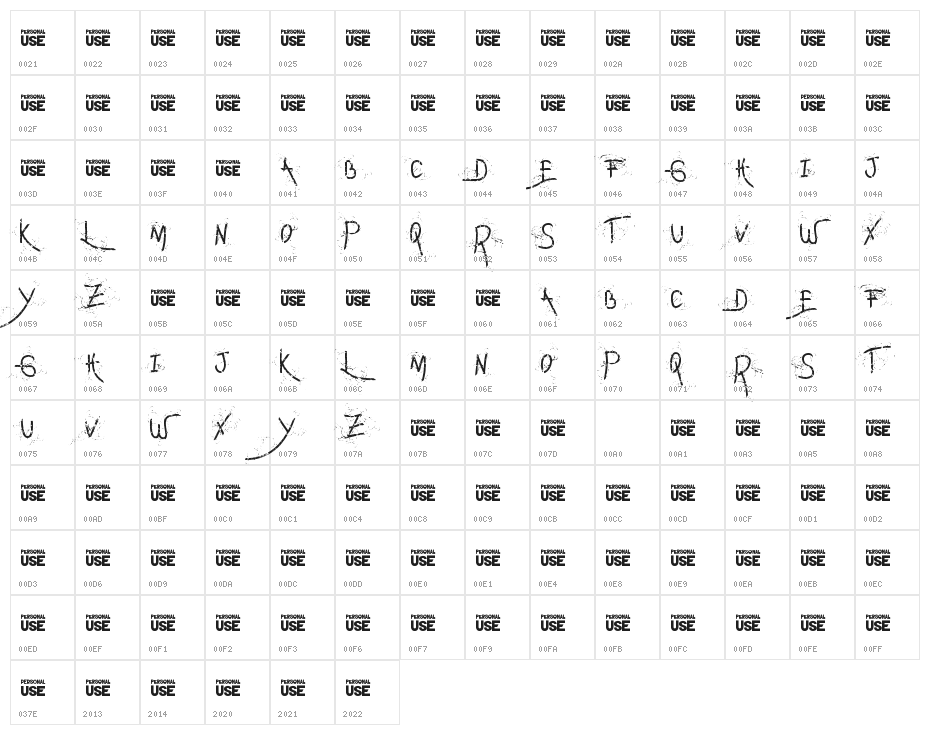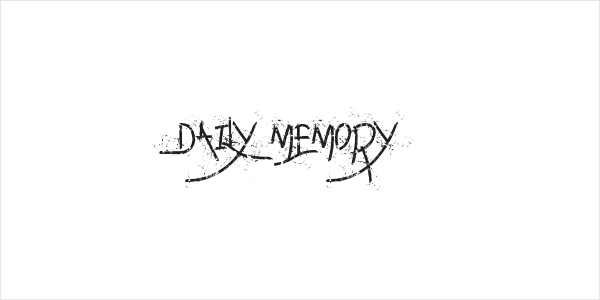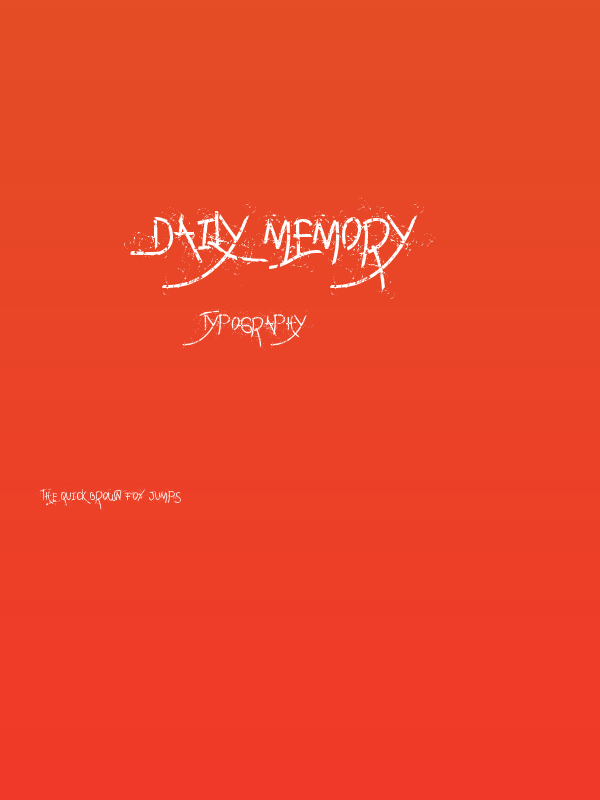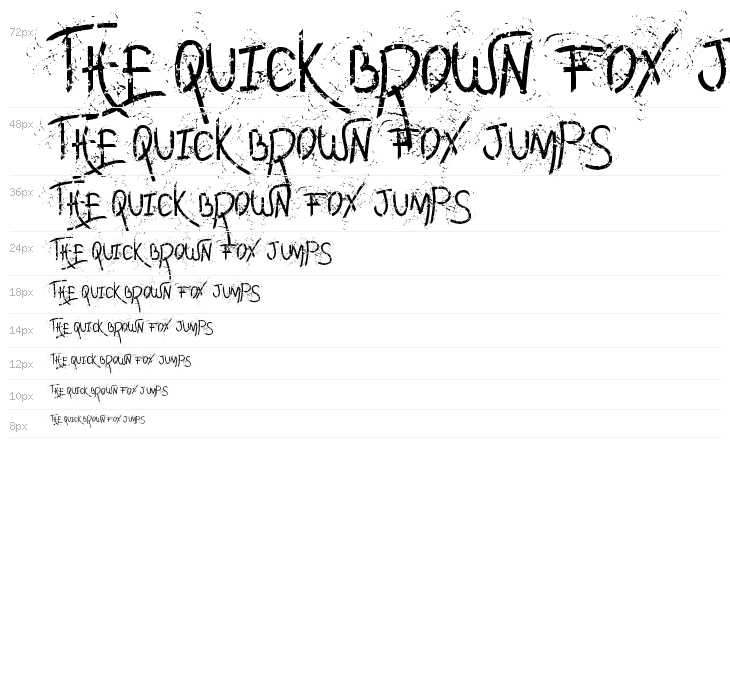
Daily memory Font
✎ Graffiti
| Gesamtstil | Urban, Edgy, Graffiti |
| Anwendungsfall | Logos, Headlines, Posters |
| Vorgeschlagene Projekte | Ideal for streetwear branding, music album covers, event posters, and urban-themed designs. |